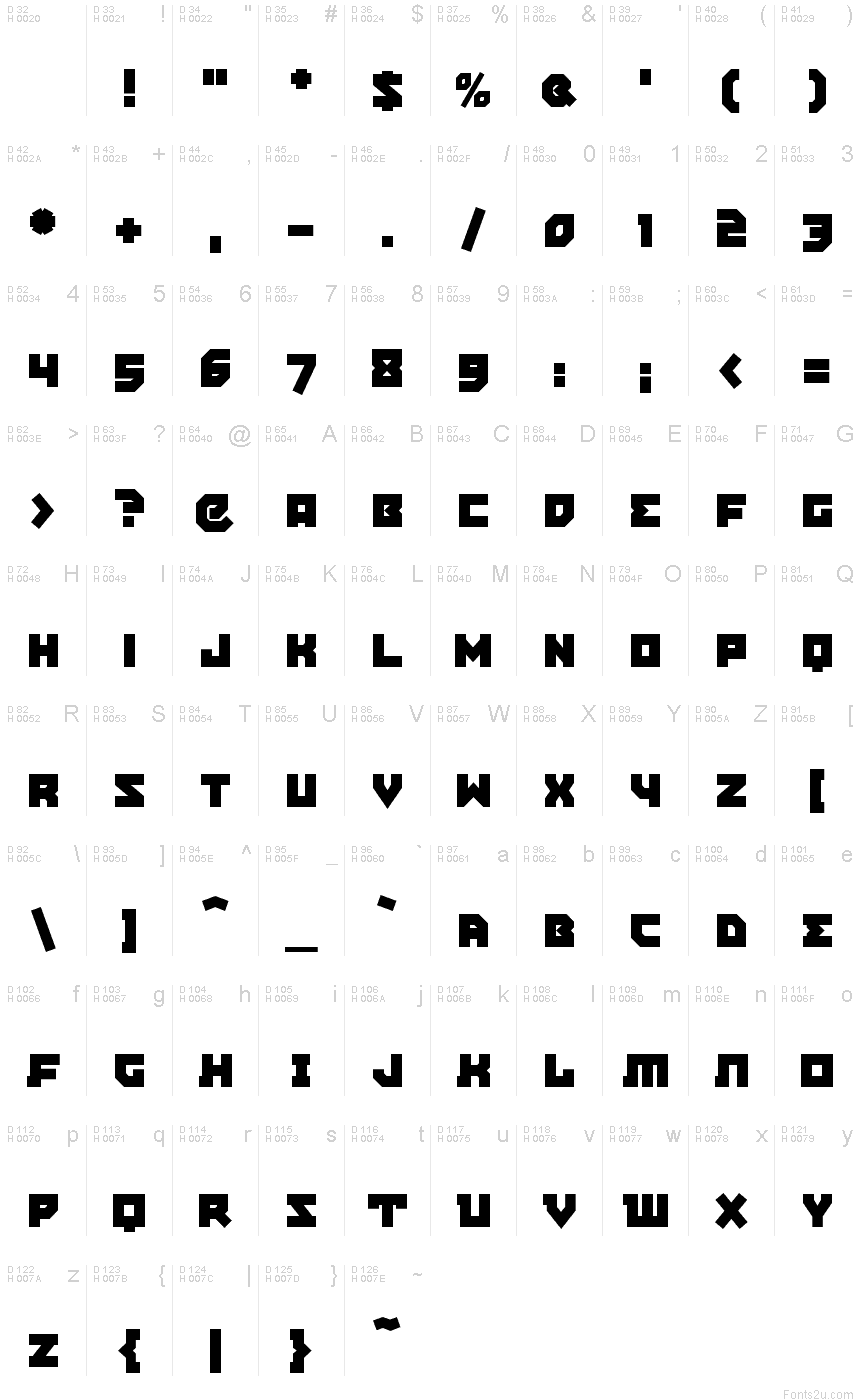
خط AgitProp Medium من تصميم Sergey Kazakov هو خط عرض (Display) تقني مجاني، يتميز بإيقاع حاد وصارم يضرب بقوة مثل صفارات الإنذار. صُممت أشكاله الكتلوية، وفراغات الحروف المربعة، والتباعد الضيق لتحدث تأثيراً بصرياً قوياً، مما يمنح كل كلمة حضوراً ميكانيكياً جريئاً يشبه شعارات الدعاية الرقمية أو لافتات الخيال العلمي.
مع AgitProp Medium، ستظهر العناوين في شعارات الألعاب، والملصقات، وأغلفة الألبومات، وهويات الرياضات الإلكترونية، وفعاليات التكنولوجيا، ورسومات الويب، بجاذبية فورية. يتألق هذا الخط المجاني عند استخدامه بحجم كبير وبوزن عريض؛ استخدم معه خطاً بسيطاً بلا زوائد (Sans) في النصوص الصغيرة للحفاظ على وضوح الرسالة، بينما يتولى AgitProp مهمة إحداث التأثير البصري الصاخب.